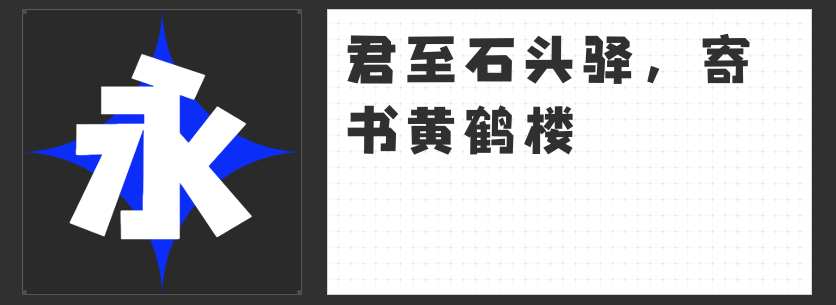
四款匠心标题字体推荐:打破常规,重塑视觉张力
在设计中,标题字体是视觉叙事的灵魂,其独特的个性与表现力往往能瞬间抓住受众目光。今天推荐的四款非免费商用字体,均以突破性设计语言为标题设计注入全新可能。
一、励字暴风简 超级黑
这款字体以解构主义重塑黑体基因,粗壮笔触中暗藏梯形分布的横竖笔画,打破传统黑体的规整框架。不规则的笔画粗细对比与梯形元素点缀,赋予文字如工业机械般的硬核质感,适合科技、潮流、运动类主题的标题设计,其强烈的视觉冲突感能瞬间点燃版面活力。
二、高手字斋东京体
东京体以“外简内达”为设计哲学,将传统方块字型与现代极简主义完美融合。锋利笔画的锐度与平滑曲线的温度形成微妙平衡,横竖排皆可呈现清晰视觉层级。其“跳出性”特质使其在信息洪流中脱颖而出,尤其适合文化、艺术、生活方式类品牌的标题表达,传递含蓄而深刻的文化张力。
三、励字逆反差圆舞简 超级黑
这款逆反差字体以“圆弧对抗直线”为创意核心,在保留方正字型的基础上,将撇捺钩点转化为饱满弧线,形成刚柔并济的视觉韵律。对称笔画与大中宫设计确保文字的易读性,而强烈的粗细对比则赋予标题戏剧化的视觉冲击,适合需要同时传递力量感与亲和力的创意场景。
四、创客贴石头体
石头体以“纸折”为灵感,将方正笔画转化为带有折叠转角的几何形态,仿佛将纸张的立体感凝固于平面。圆润的折角与方正的骨架形成趣味反差,营造出天真烂漫的视觉氛围。其可爱风格尤其适合儿童、文创、轻食等领域的标题设计,用最简洁的形态传递最纯粹的快乐。
四款字体虽风格迥异,却共同诠释了当代设计对“破界”的追求。它们都能以独特的视觉语言,为标题设计赋予超越文字本身的叙事能量。